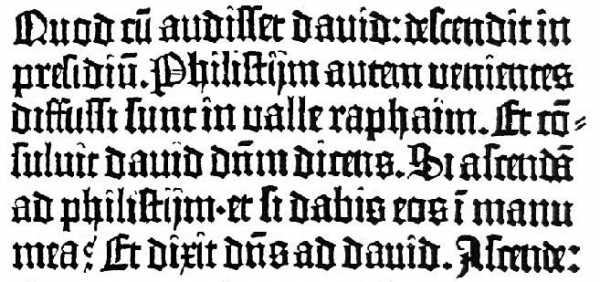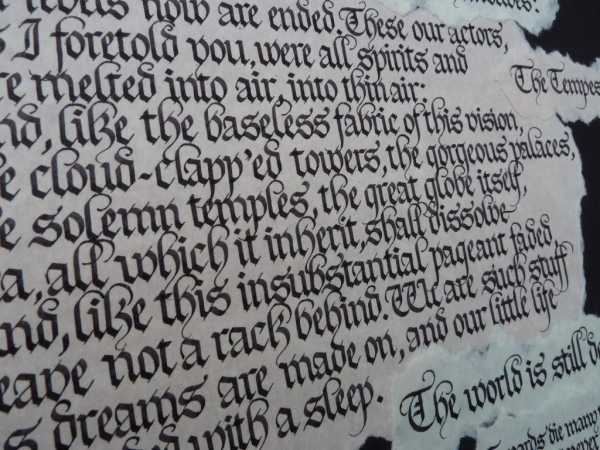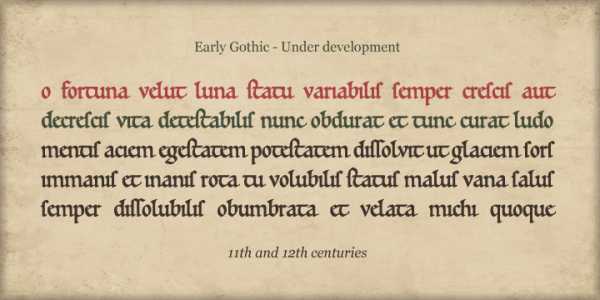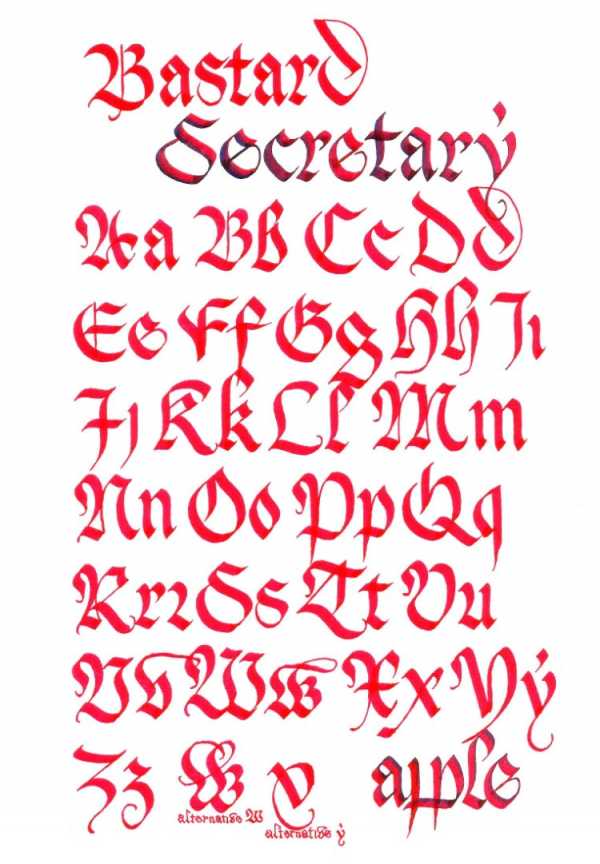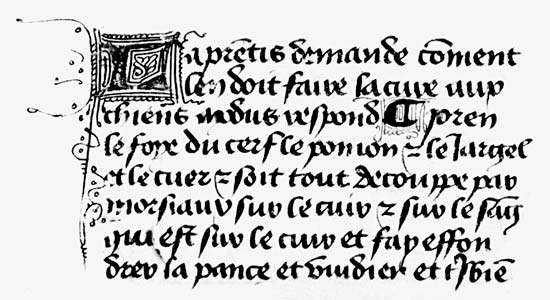
Древний готический шрифт – Готические шрифты | Шрифты онлайн
В какой стране возникло готическое письмо? Характерные черты готического шрифта
Начиная с конца XI столетия в характере устоявшегося каролингского унциального письма происходят изменения: написание литер становится уплотненным, надламываются их округления и более усиливается вертикальный штрих. Концентрация читающего стала переноситься с отдельной буквы на образ слова. Появившийся готический шрифт определил новую историческую веху.
Готическое письмо
Слово или текст в зависимости от начертания букв могут производить всевозможные эмоциональные впечатления. Готическое письмо, представляя собой семейство рукописных шрифтов латинского письма Средневековой эпохи, навевает некий покров таинственности и силы. Используя подобные шрифты, автор передает адресату не только информацию, но и формирует причастность к древним традициям или соответствующей эпохе. Таким приемом успешно пользуются антикварные магазины, производители религиозных изделий и западноевропейские газеты, оформляя названия и заголовки готическим шрифтом.
Своим наименованием, которое появилось значительно позднее, готическое письмо обязано древнегерманскому союзу племен – готам. Гуманисты итальянского возрождения XV века посчитали шрифты варварскими и в именовании данной письменности выказали свое негативное отношение, противопоставляя ей древнеримскую.
Появление готического шрифта
В какой стране возникло готическое письмо? В этом вопросе многие склоны упоминать Германию, связывая ее с тем, что поздняя готика была сформирована именно там. Но по сохранившимся источникам и некоторым исследованиям историков-искусствоведов, первые образцы стиля зародились в монастырях на севере Франции к середине XI века. На основе латинского алфавита при непрестанной переписке рукописей Священного Писания стал проявляться новый тип письменности — остроконечное монашеское письмо. Образ букв менялся, в нем стали появляться надломленные черты, при этом вертикальные линии все больше усиливались по отношению к связующим, пока те не стали едва заметными.
Появление нового стиля вполне могло быть спровоцировано дороговизной бумаги и пергамента того времени, а также сложностью их изготовления или возможностью стандартизировать буквы, свести к минимуму разницу нескольких почерков в одной книге.
Ранний готический шрифт (или протоготический) распространился в западной Европе и широко использовался до середины XIII столетия.
Отличительные черты
Общий вид символов готической письменности определялся использованием гусиных перьев как пишущих средств, которые в зависимости от среза и наклона (45 градусов) выдавали соответствующие линии. Основной особенностью письма служила строгая параллельность штрихов между собой, которая включала все элементы (жирные и волосные черты, угловые изгибы). Такие буквы готического шрифта, как m, n, u и i, представляли собой вертикальные доли (например, minim). В случае, когда слово включало все указанные литеры, прочесть его становилось крайне затруднительно.
Склонность к уплотнению строки стала характерной для готического письма, она выразилась и в слиянии прилегающих между собой соединительных линий. Теперь находящиеся рядом буквы o и e преобразовались в такую конструкцию, что процесс чтения значительно усложнялся.
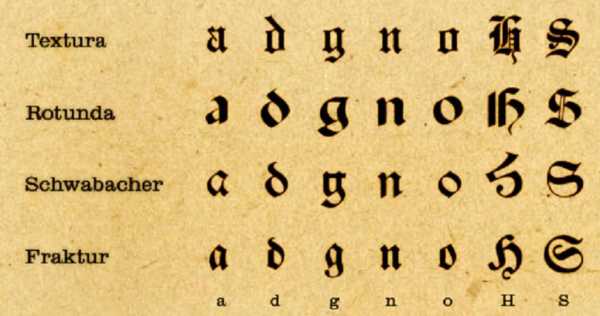
Основные виды готической письменности
Готическое письмо за время своей истории обрело множество вариантов. В разных государствах, сохраняя общую узнаваемость, готический стиль обрастал специфическими свойствами, и шрифты приобретали свои индивидуальные названия. Шрифт, дошедший до нынешнего времени, возник усилиями немецких каллиграфов в XV столетии.
Текстура (от латинского textualis — ткань) является основной разновидностью готической письменности. Вытянутость прописных латинских букв дает характерное отличие данного шрифта. Текст равномерно и уплотненно покрывает весь пергамент, создавая картину темного письма, напоминающего ткань.
Ротунда (от итальянского rotonda — круглая) представляет итальянскую разновидность готического письма, появившеюся в XII веке. Данный шрифт отмечается округленностью написания символов и отсутствием надломов в линиях.
Фрактура (от латинского littera fractura – ломаная буква) представляет один из поздних стилей германской готической письменности, появившийся в конце XV века. Для этого вида письма присущи остроконечные ломаные очертания. В последующие века фрактура становится доминирующим стилем в странах Северной Европы.
Готический стиль в русской письменности
Славянские шрифты, в отличие от латинских, пошли по совершенно иному пути развития. Взгляды ученых достаточно противоречивы на этот счет, поэтому большинство вопросов на сегодняшний день остаются открытыми.
В русском письме готический стиль нашел слабое отражение в круглой вязи (1497 год), которая применялась в ранних печатных изданиях на Руси. Сочетания и компоновки букв готического характера хорошо прослеживаются в написании слов этого шрифта. Известно, что на первых порах вязь использовалась лишь в заголовках в виде соединения нескольких переплетающихся литер, но вскоре ею писались уже целые строки. Как и готическое письмо, вязь очень трудно читалась.
- текстура (нем. Textur, лат. textualis) — острое письмо;
- фрактура (нем. Fraktur) — острое письмо с ломаными очертаниями;
- швабахер (нем. Schwabacher) или бастарда — ломаное письмо с округлёнными очертаниями некоторых букв;
- ротунда (итал. rotunda или круглоготическое нем. Rundgotisch) — переходный вид письма от готического к антикве;
- куррент — готический курсив; с начала XX в. в качестве стандартного готического курсива принят шрифт Зюттерлина.